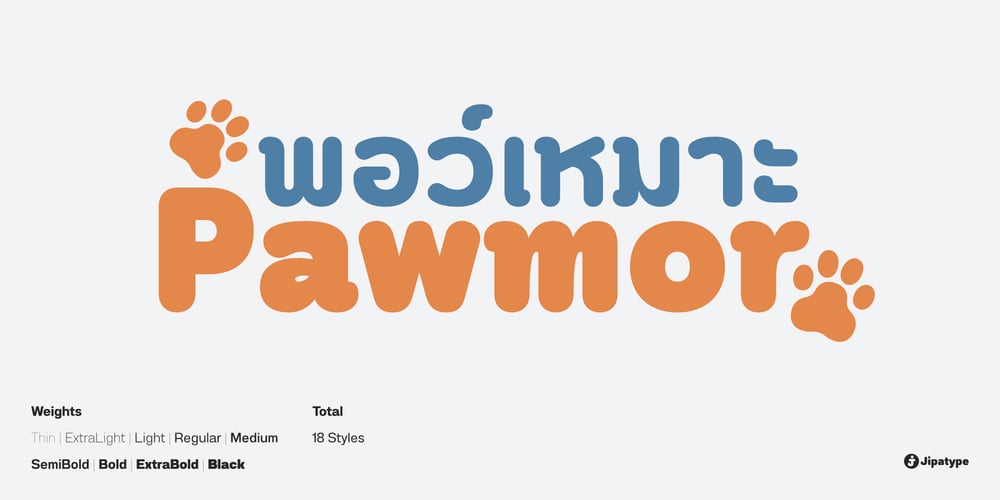
Pawmor
Pawmor font
Pawmor Font Family was designed by Anupap Jaichumnan and published by Jipatype. Pawmor contains 18 styles and family package options. ขอแนะนำ Pawmor ฟอนต์ sans-serif ใหม่ที่น่ารักและขี้เล่น ซึ่งจะเพิ่มความน่ารักให้กับงานออกแบบของคุณ! แบบอักษรนี้เหมาะสำหรับโปรเจ็คที่เกี่ยวข้องกับสัตว์เลี้ยงหรือสัตว์ต่างๆ ด้วยขอบที่โค้งมนและส่วนโค้งที่นุ่มนวล ให้ความรู้สึกอบอุ่นและเป็นกันเองจนยากจะต้านทาน Pawmor มีให้เลือกถึง 18 แบบ ให้คุณได้เลือกใช้ตามความต้องการของคุณ ด้วย Pawmor คุณสามารถสร้างงานออกแบบที่สะดุดตาสำหรับธุรกิจเกี่ยวกับสัตว์เลี้ยง งานกิจกรรมต่างๆ เกี่ยวกับสัตว์ โดยรวมแล้ว Pawmor เป็นตัวเลือกที่สมบูรณ์แบบสำหรับทุกคนที่ต้องการเพิ่มความแปลกใหม่และความสนุกสนานให้กับงานออกแบบของคุณIntroducing Pawmor, the adorable and playful new sans-serif font that will add a touch of cuteness to your designs! This font is perfect for any project that revolves around pets or animals. With its rounded edges and soft curves, it exudes a warm and friendly vibe that’s hard to resist. Pawmor comes in 18 different styles, giving you plenty of options to choose from. With Pawmor, you can create eye-catching designs for pet-related businesses, animal-themed events. Overall, Pawmor is the perfect choice for anyone looking to add a touch of whimsy and playfulness to their designs